W dzisiejszym artykule podsumuję ostatnie wydarzenie, które prowadziłam na żywo „4 tygodniowy kurs hand letteringu”. Założeniem kursu było przeprowadzenie uczestniczek przez podstawowe kroje pisma oraz metody tworzenia prostych grafik i napisów technikami hand letteringu. Chciałam pokazać jakim fajnym hobby jest hand lettering i zachęcić większą rzeszę ludzi do tego cudownego zajęcia. Umiejętność pięknego pisania liter zanika, dlatego tym bardziej ważne jest, aby kultywować tę sztukę rysowania pięknych liter.
Organizacja kursu hand letteringu
Spotkania odbywały się o godz. 20 i starałam się zawrzeć całość materiału w 60 minutach. Nie znosze gdy ktoś marnuje mój cenny czas, dlatego miałam taki cel- aby nie rozciągać, nie przedłużać, i zebrać całość przekazu w skondensowanej formie. Chciałam, aby ustalony czas był zachowany, i jeśli ktoś ma tylko godzinkę i poświęca ją właśnie mnie- to niech będzie to ta godzinka. Zależało mi, aby uczestniczki poznały nowe techniki, proste kroje pisma i gotowe rozwiązania, ale nie chciałam podawać wszystkiego na tacy. Wiem z doświadczeń szkoleniowych, że tylko wtedy, gdy jesteśmy zmuszeni, aby coś wymyślić, lepiej to zapamiętujemy i pobudzamy naszą kreatywność. Dlatego karty pracy były krótkie i zawierały jedynie najważniejsze przykłady. Przed każdym spotkaniem uczestniczki otrzymywały karty pracy do druku, a po spotkaniach zadanie domowe.
Spotkanie 1: materiały do pracy
Rynek produktów biurowych jest przesycony. Znajdziemy tysiące pisaków we wszystkich kolorach tęczy. Producenci kuszą nowymi opakowaniami, nowymi modelami i osobom początkujących bardzo ciężko się w tym odnaleźć. Ja jestem absolutną zwolenniczką zasady – zacznij do minimum, zobacz czy ci się to podoba i dopiero potem decyduj, czy chcesz dalej to kontynuować. Jak to mówią „złej baletnicy przeszkadza rąbek spódnicy„, dlatego wystarczą ci 1-2 modele. Ja od lat zachęcam rozpocząć naukę od pentel touch lub/ i edding brush pen 1340. Więcej naprawdę nie potrzebujesz. Najpierw technika, potem eksperymenty, dopieszczanie i wspinanie się coraz wyżej.
Spotkanie 2: Kroje pisma na start
W dzisiejszych czasach oczekujemy postępów i efektów od razu- natychmiast w tej chwili. Podczas spotkania pokazuję 4 proste kroje, które możesz wykorzystać od razu. Są proste, a równocześnie ładne.
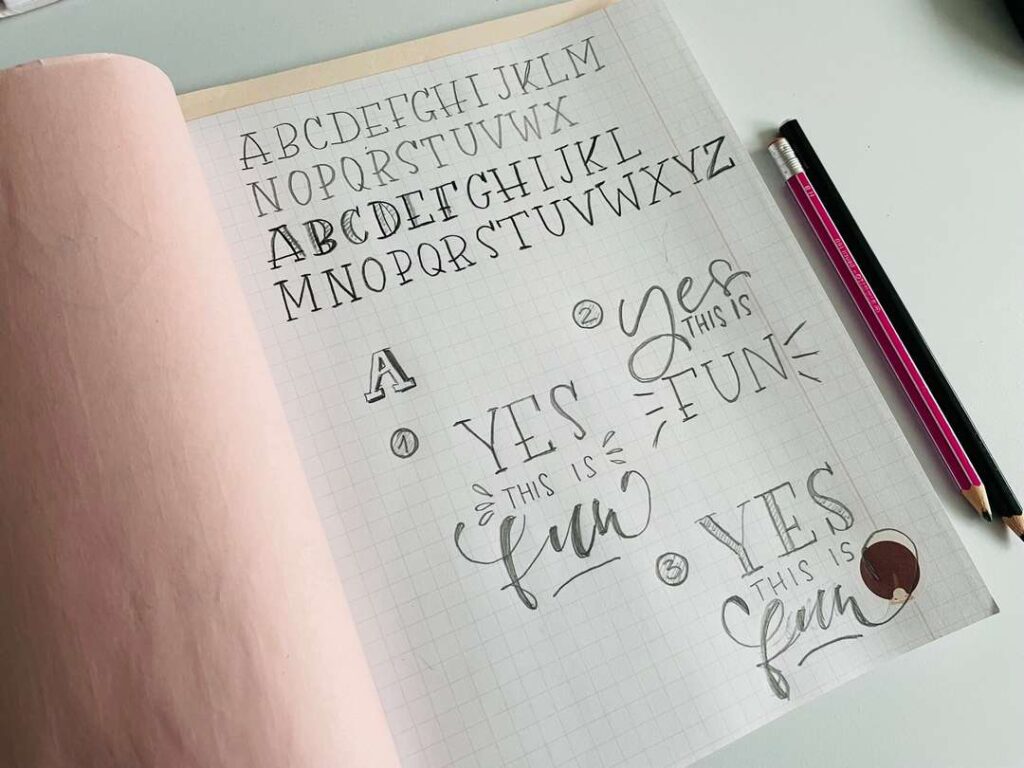
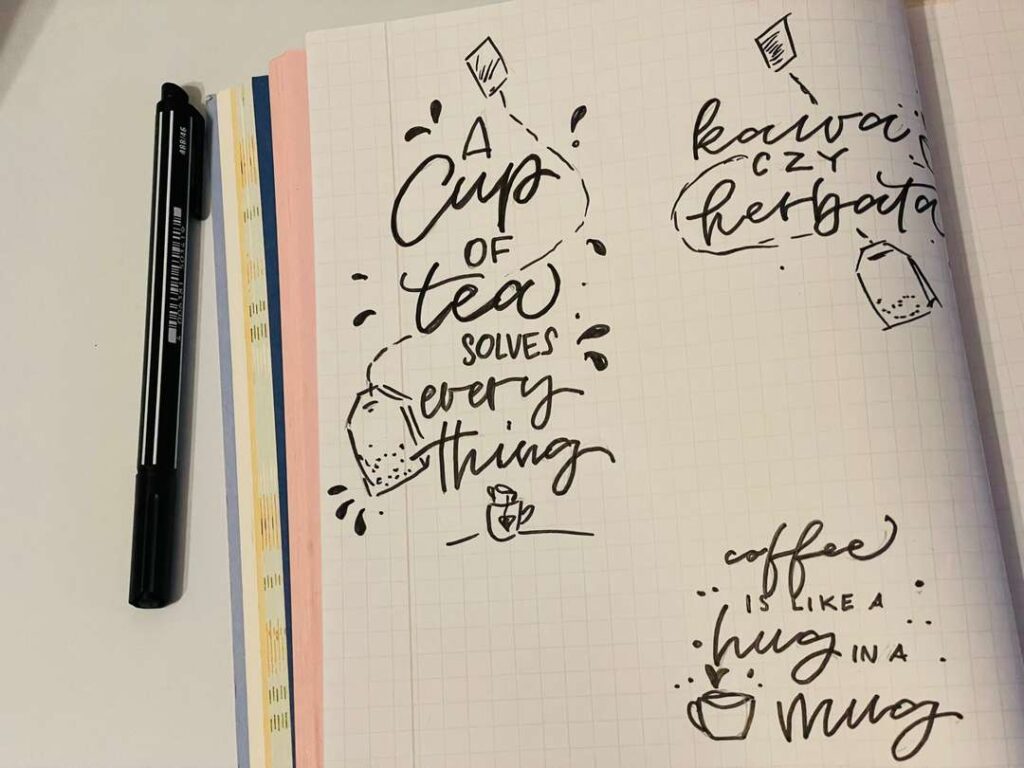
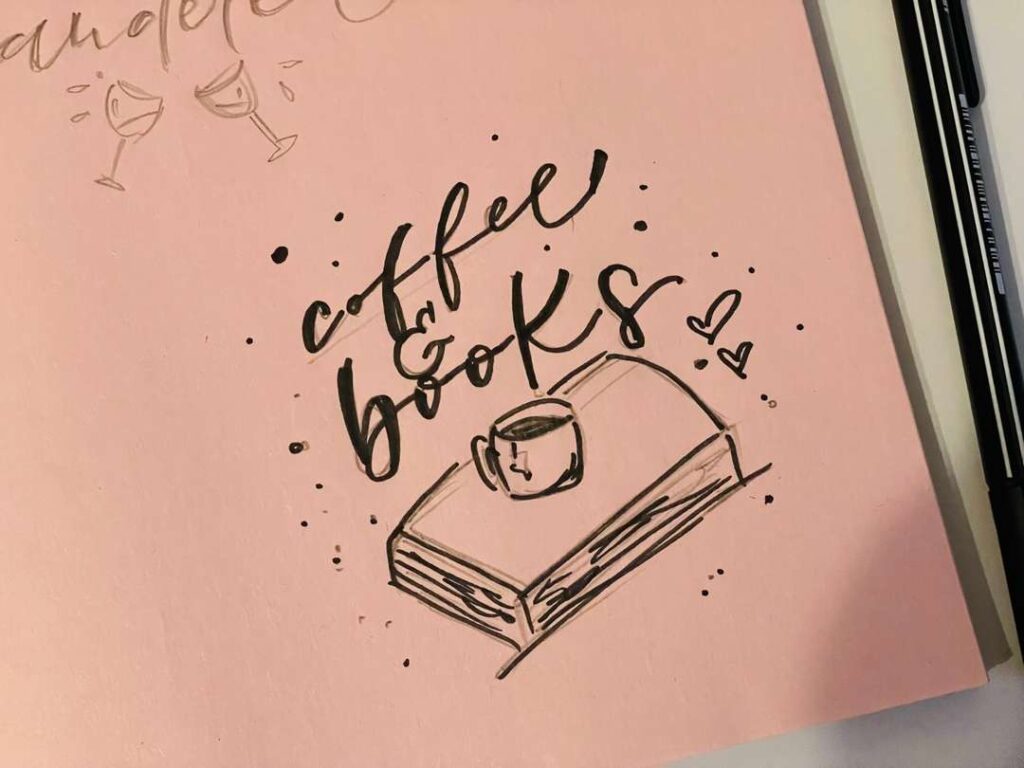
Spotkanie 3: Brush lettering
Brush lettering to mój ulubiony krój pisma w hand letteringu. Na spotkaniu przerobiłyśmy podstawowy alfabet i napisałyśmy kilkanaście wyrazów.
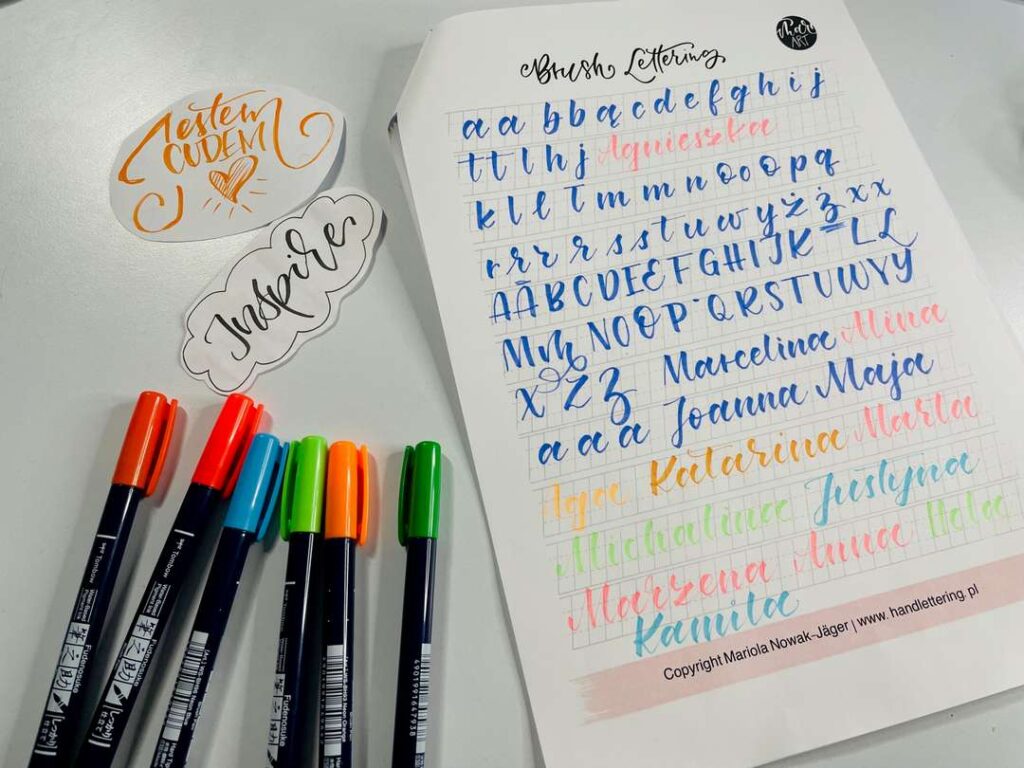
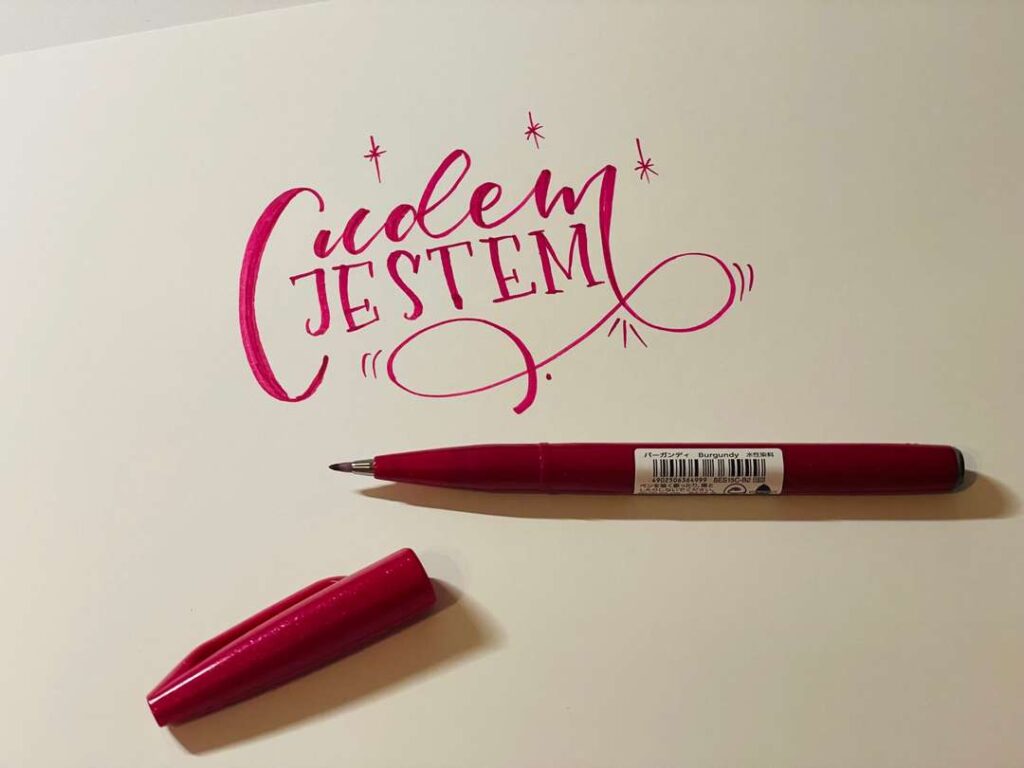
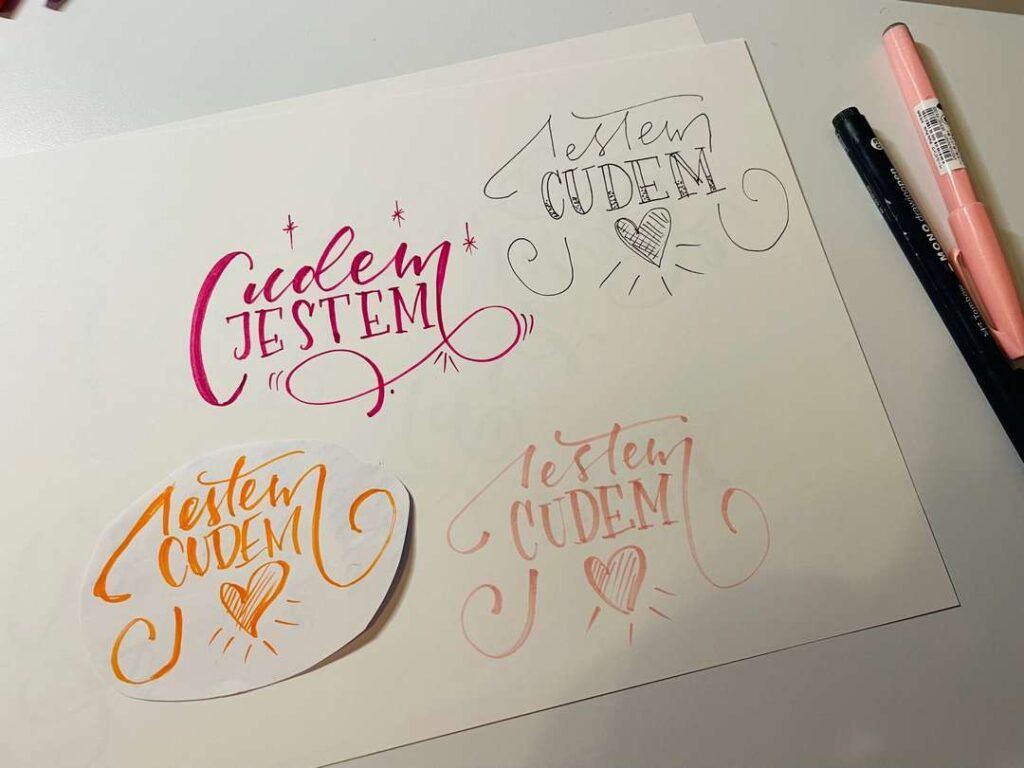
Spotkanie 4: Dekorujemy litery
Na spotkaniu pokazałam kilka podstawowych sposobów dekorowania liter.
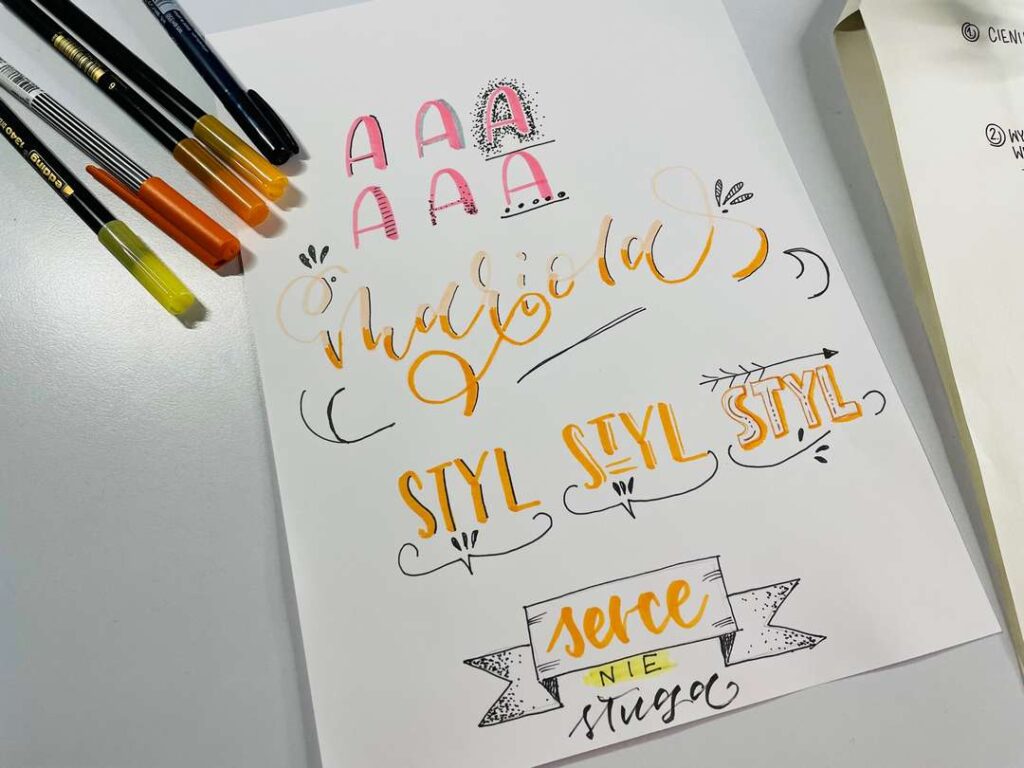
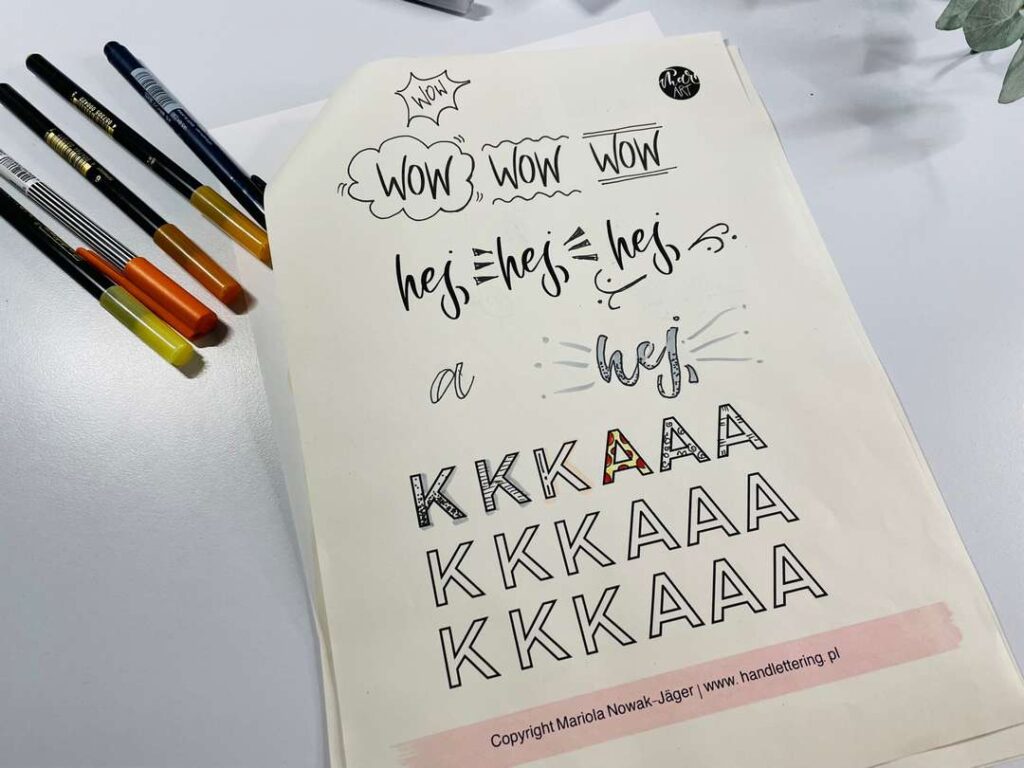
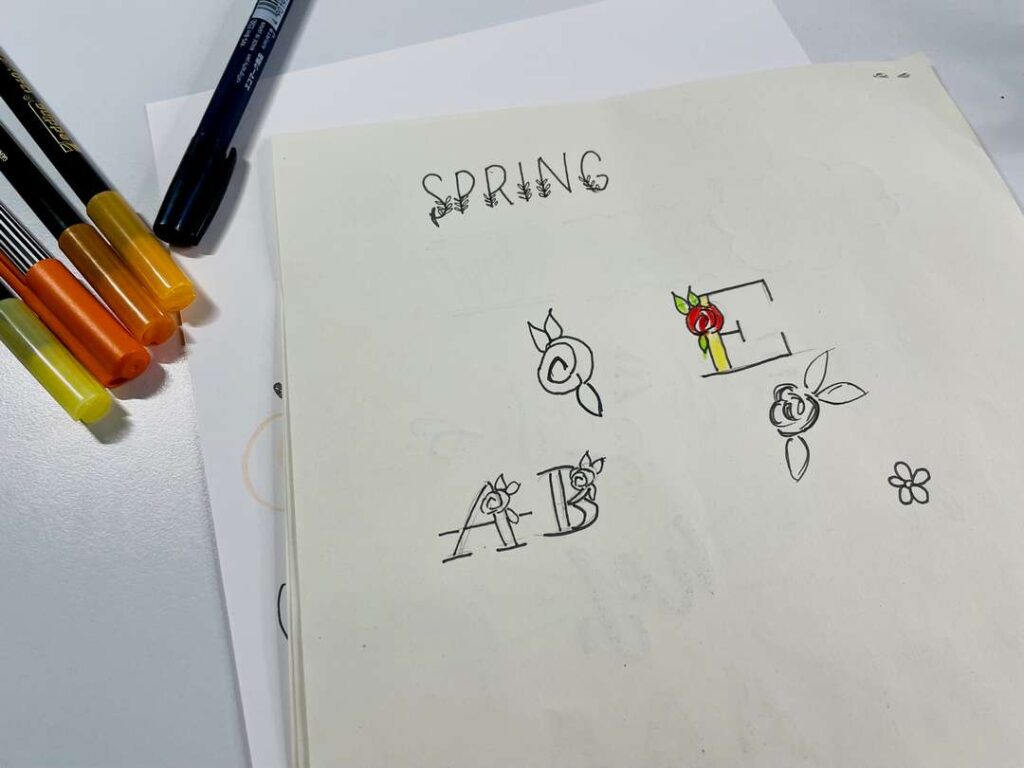
Prace kursantek
Marta: